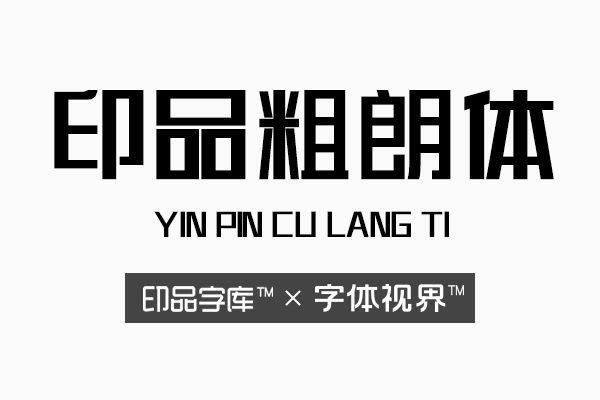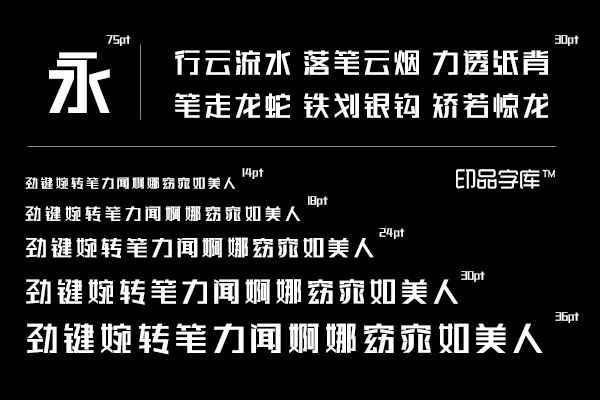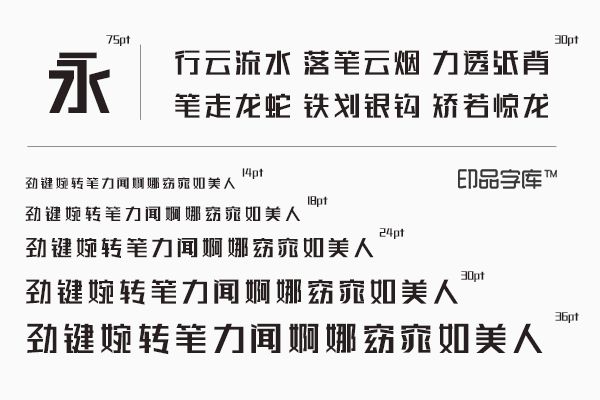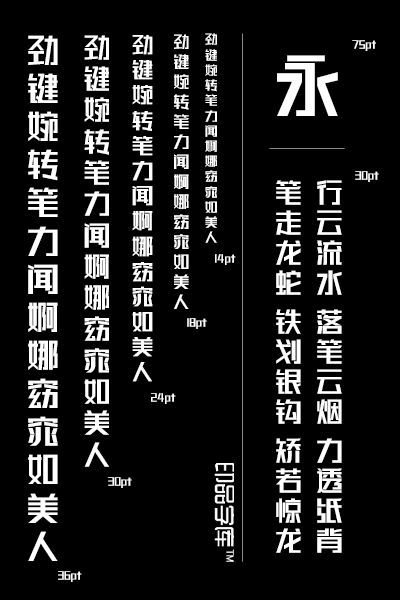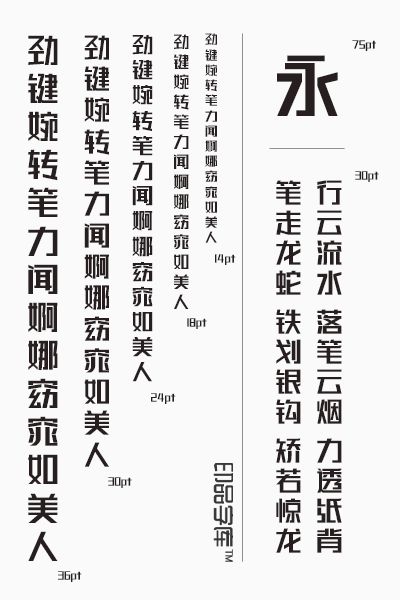
都说精灵是天使,所以受到大家的喜爱,那么像它一样有着灵气的字体又会有怎样待遇呢。那像印品粗朗字体这样充满字体设计感的字体应该也受到大家的喜爱才合理吧。她一直这么想。
“你到底是什么呢?”已经不同于初遇时的惊恐,她已经能平静的问出她问过一遍又一遍的问题了。然而另一位当事者却只是一如既往地在她面前扑腾着晶莹剔透的翅膀,那双大大的眼睛里写满了无辜。
突然一阵敲门声响起,“快,来人了”它瞬间钻进了她的书包里。“这次还挺快”送走突击检查的妈妈后她拍拍书包,似是安抚。它探出小小的脑袋,不知道为什么,她觉得它是有话要说的。
已经适应生活中有它的存在了,它成了她的闹钟,每天早上将她啄醒。她也成了它的守护神,躲过了一次次不必要的惊吓和麻烦。
只是没想到这样的生活结束的如此突然。她感到心里似是有什么空缺。
后来,她接触到了像它一样灵动的字体时,她感受到久违的温暖。
带着古灵精怪特质的印品粗朗体给人气质不凡的感觉。字体结构清晰,字体笔画的设计上的大小不一也体现了设计者想展现的俏皮和可爱。
这类字体就像精灵般给阅者带来轻灵的感受。这种个性中文艺术字体,适用范围广泛,面向各年龄段的消费群体。适用于各类阅读体验。